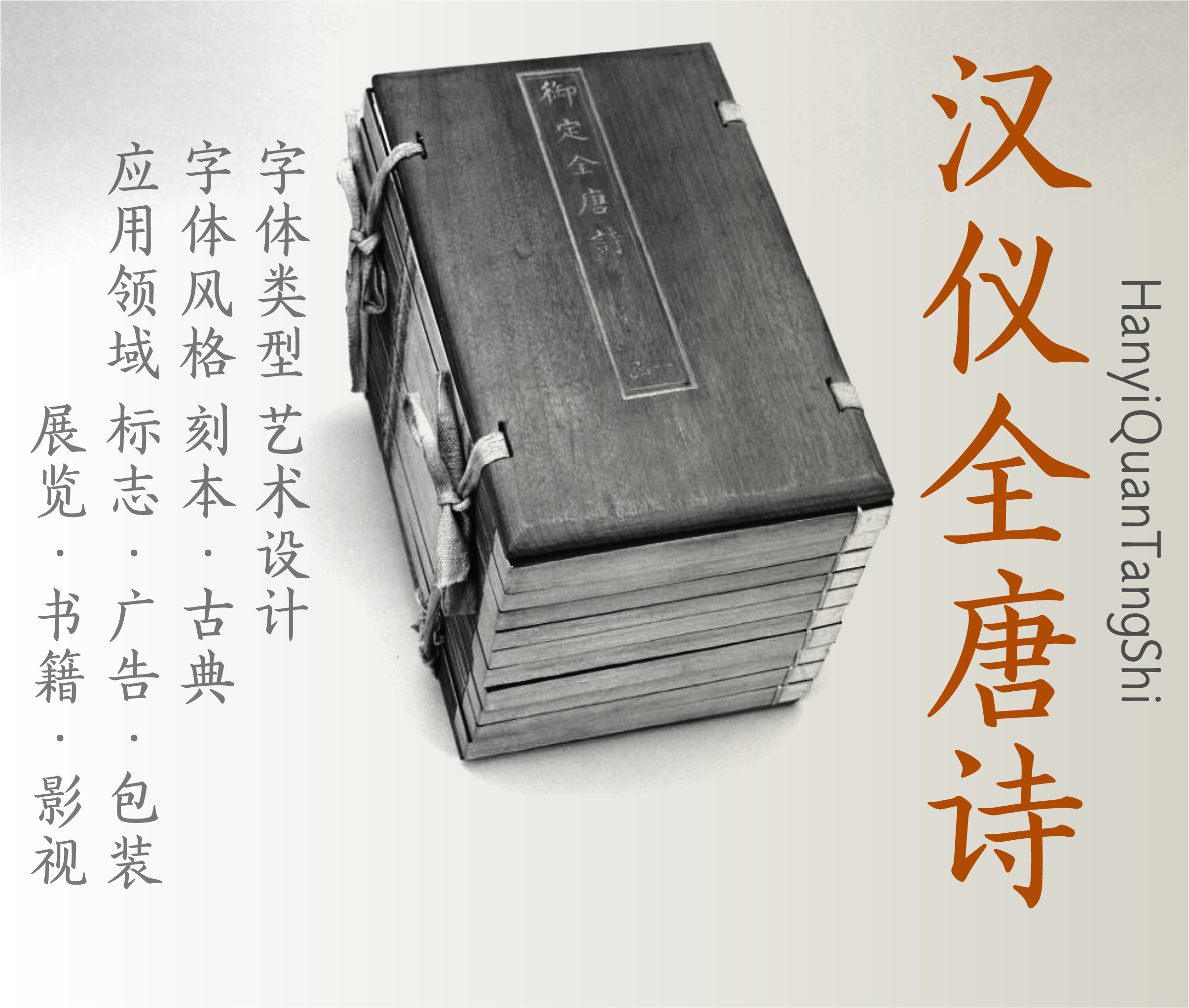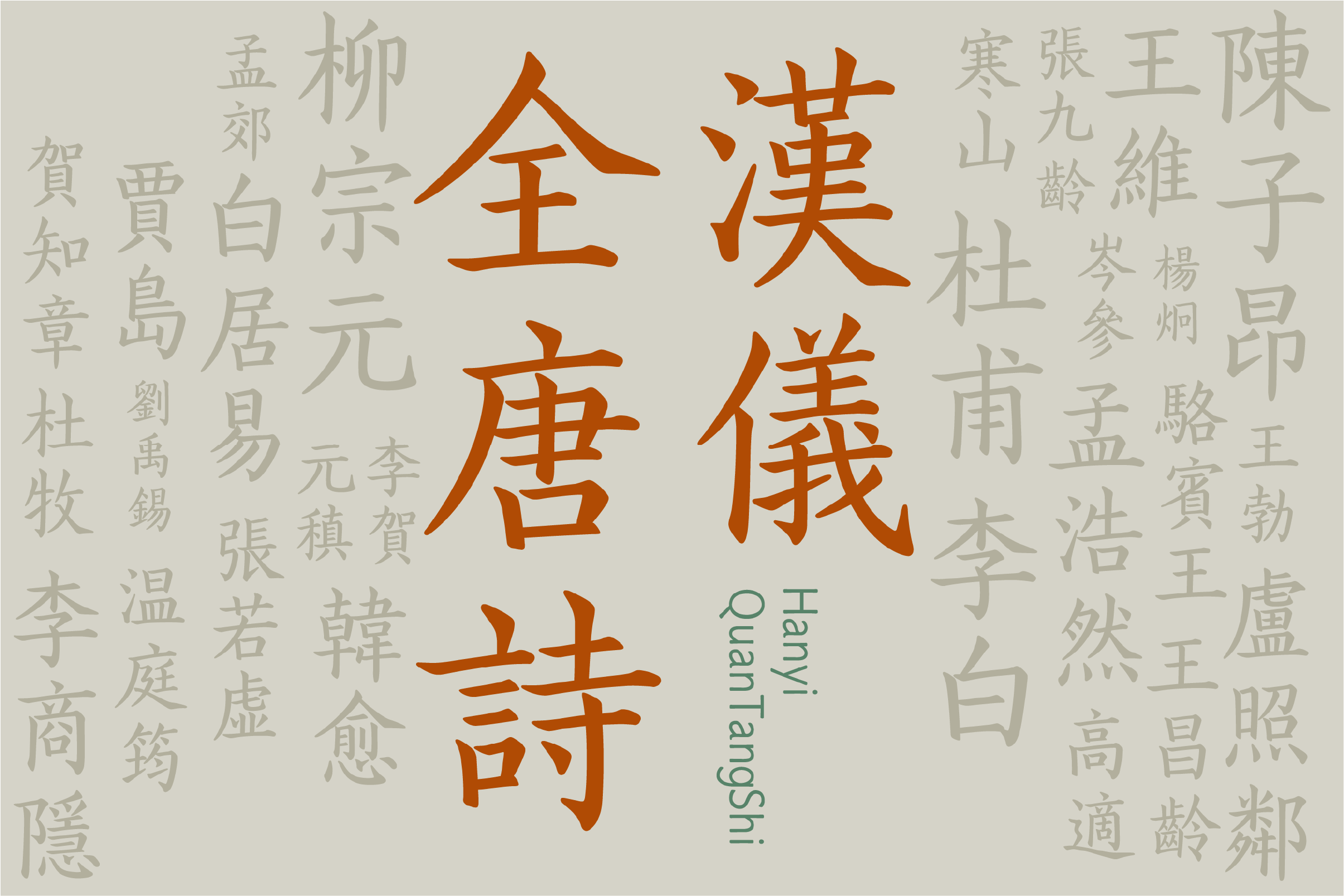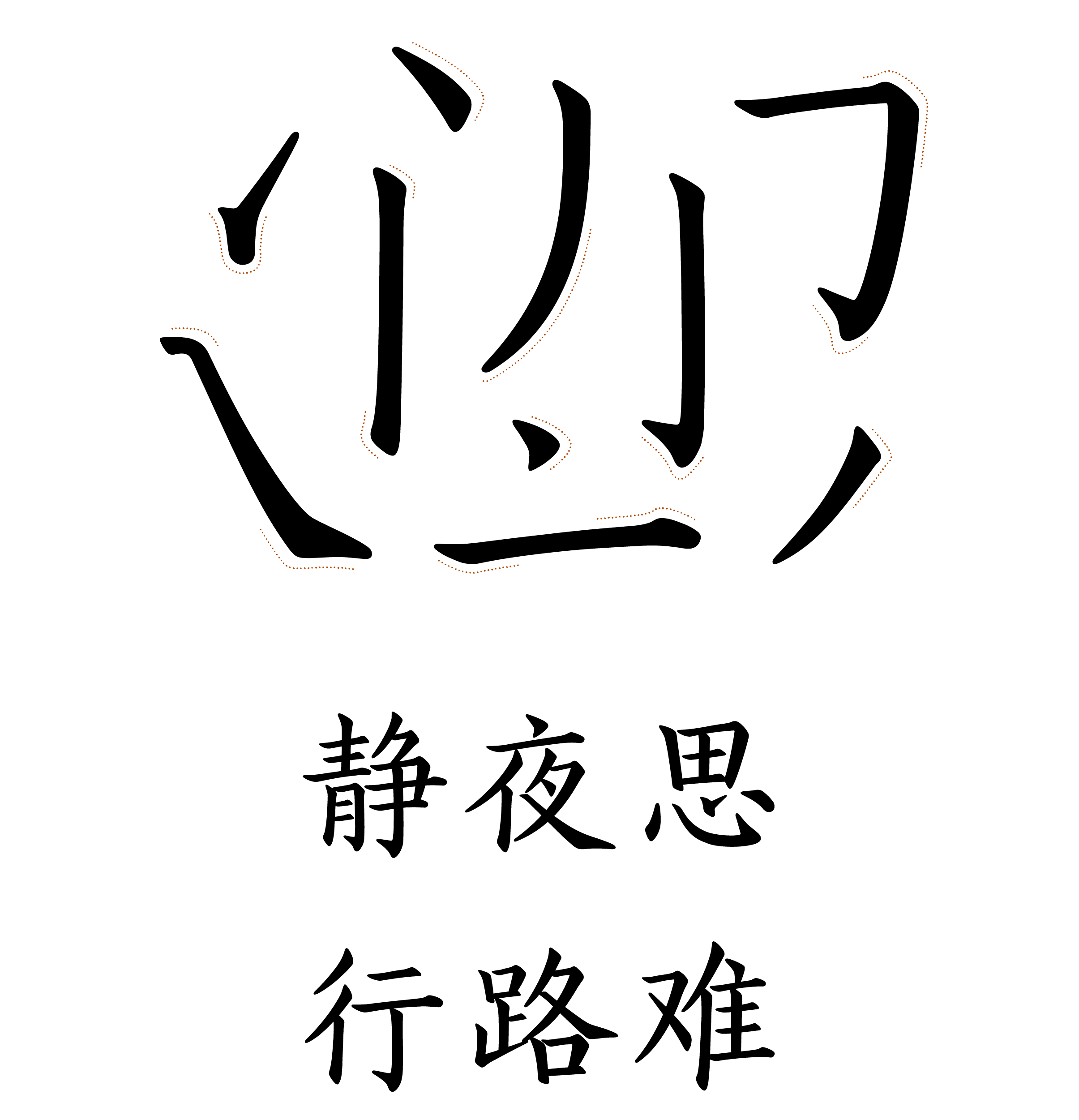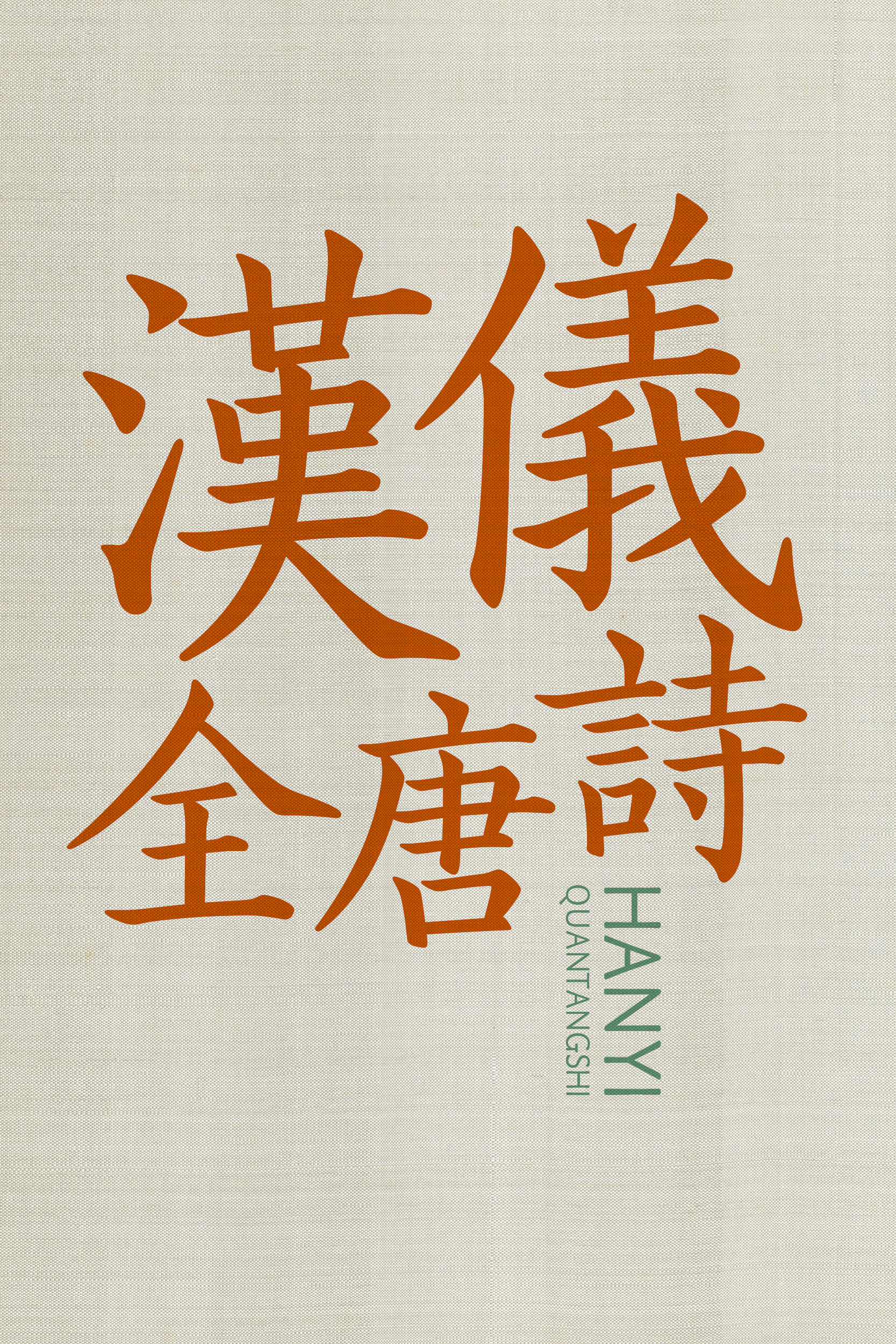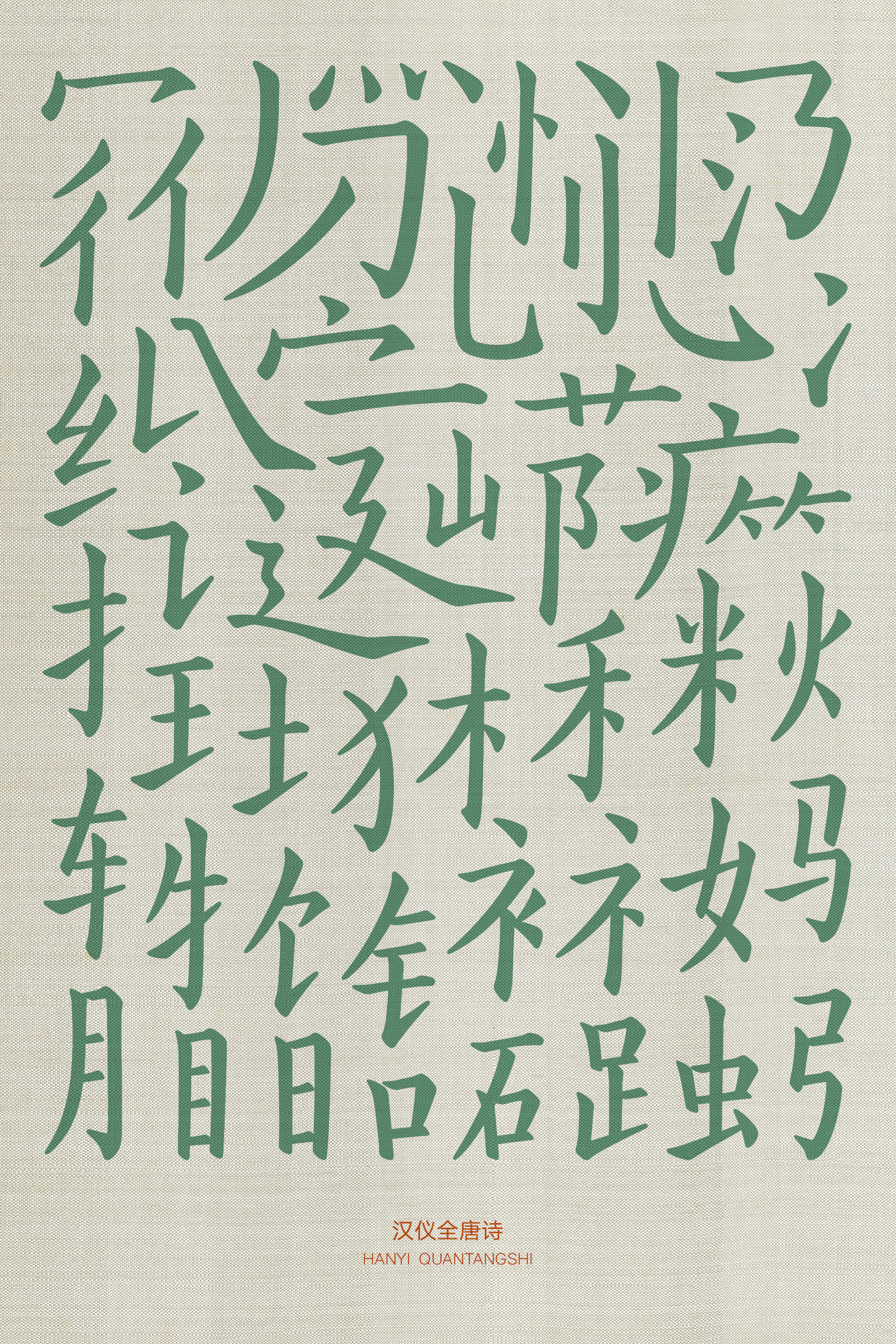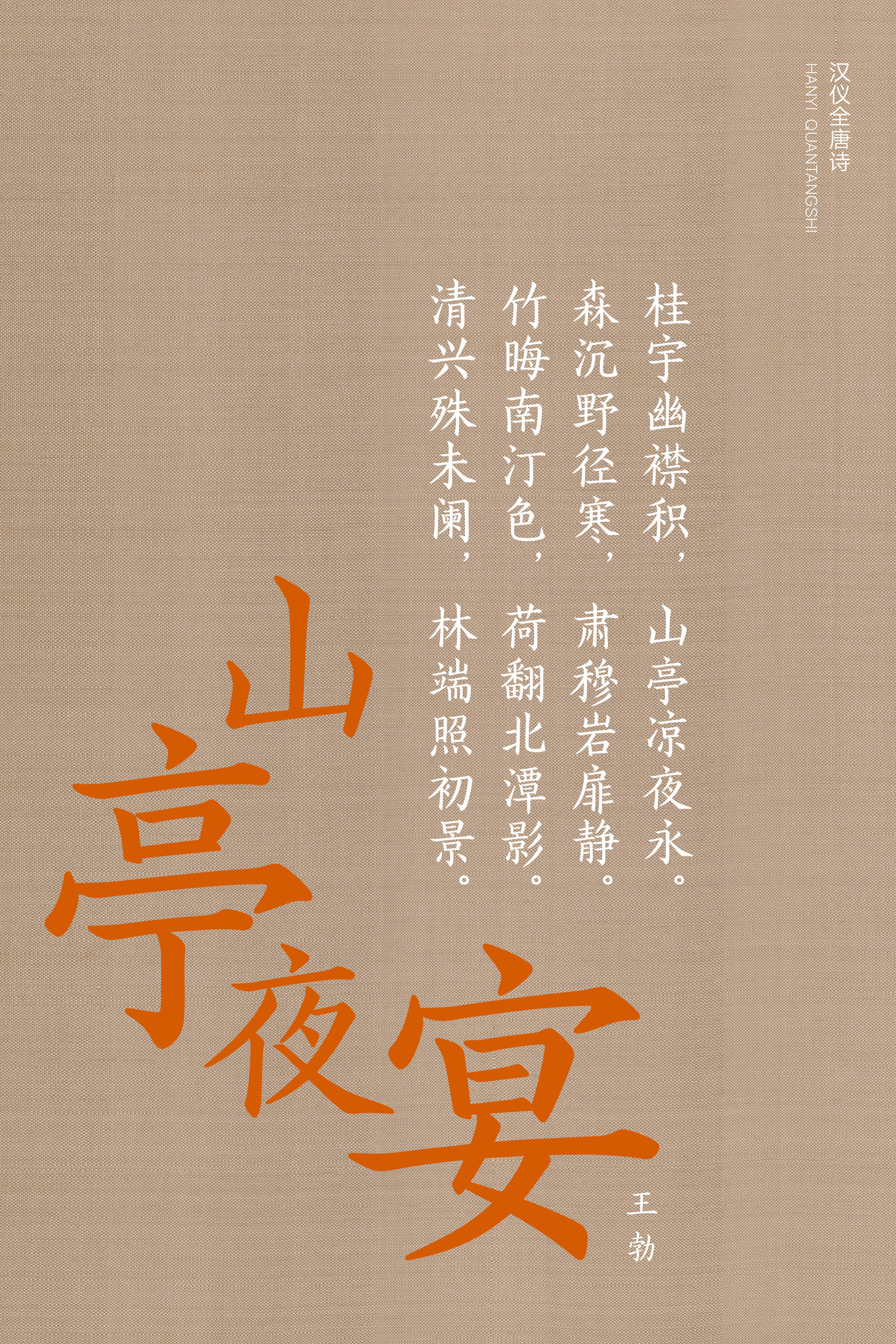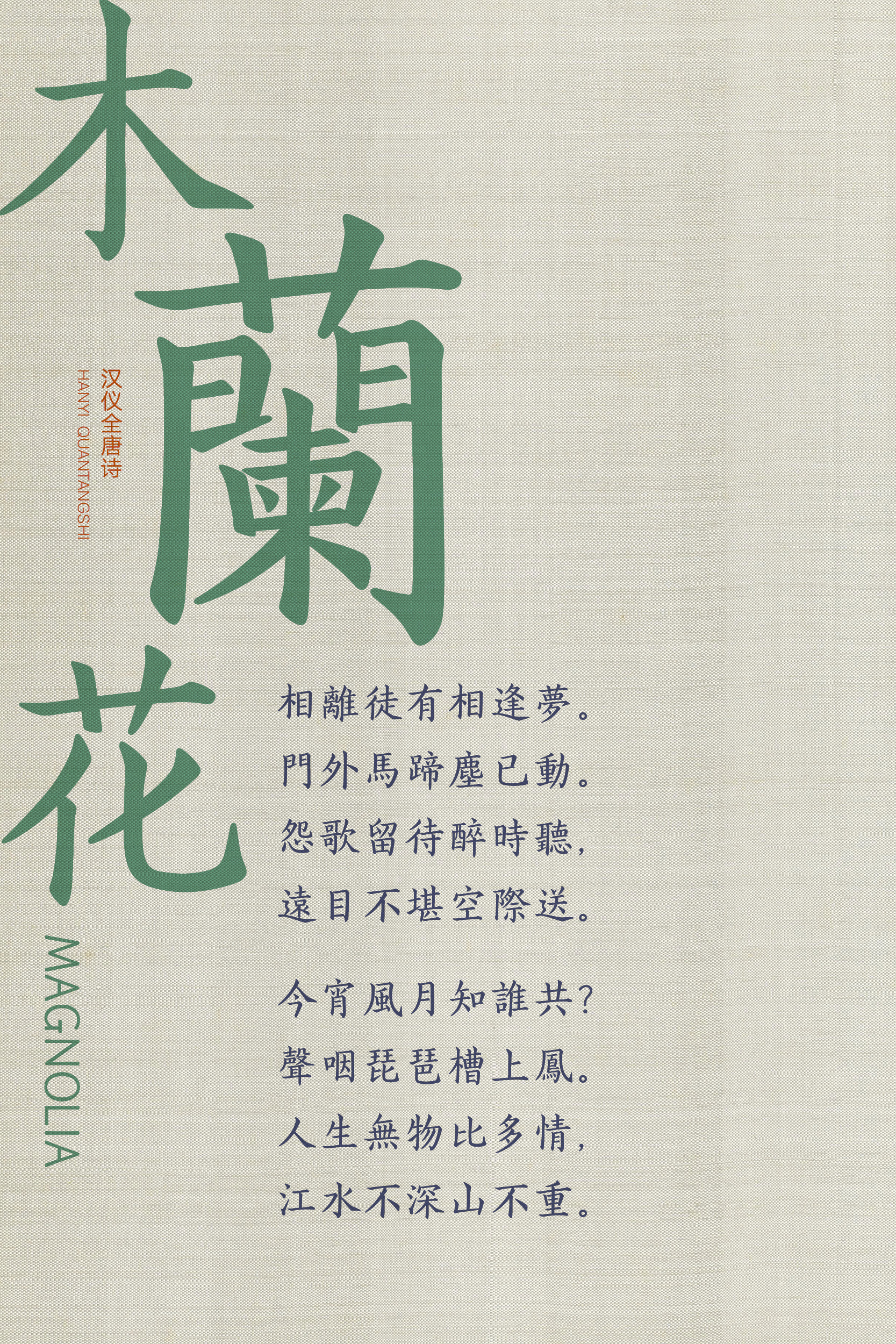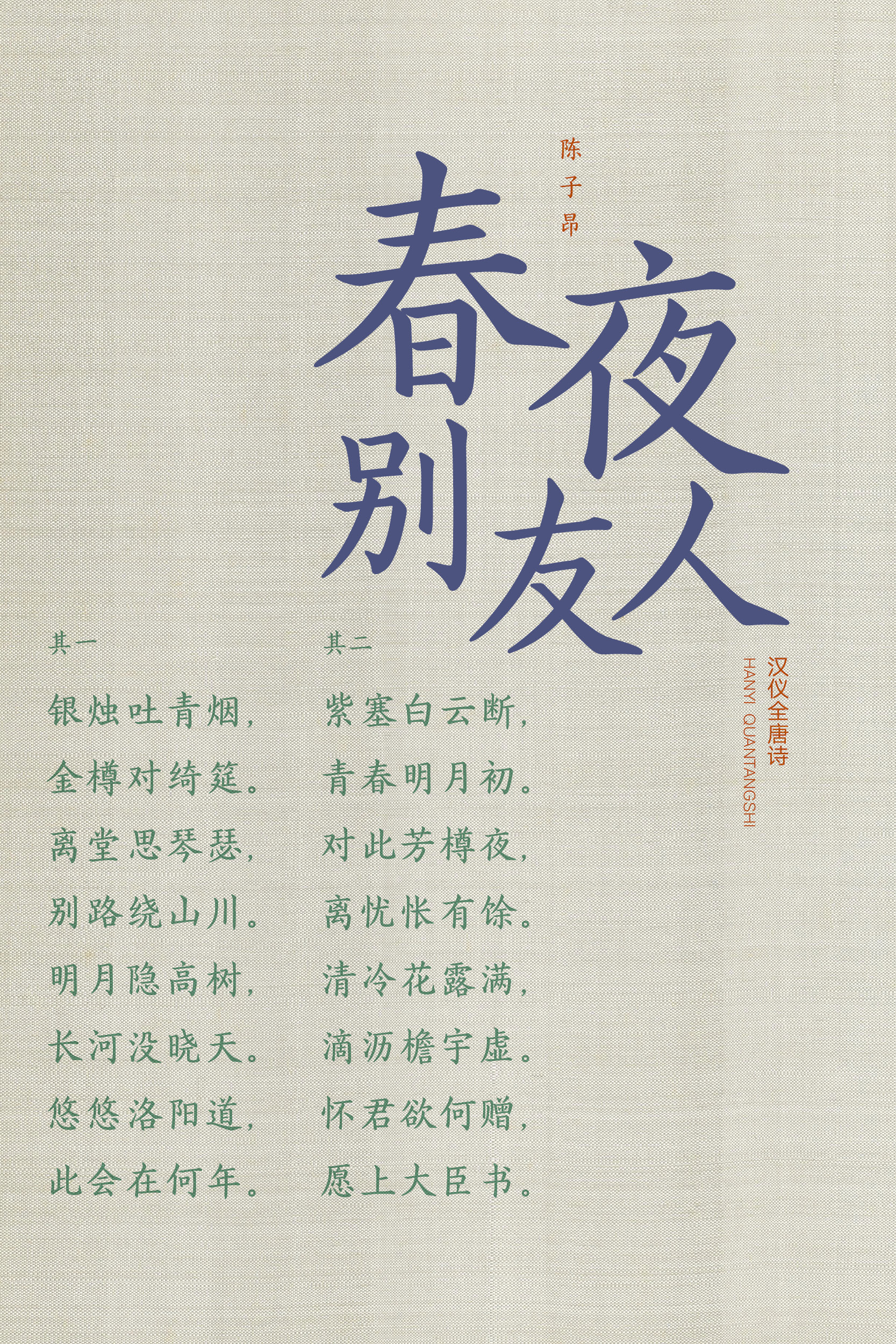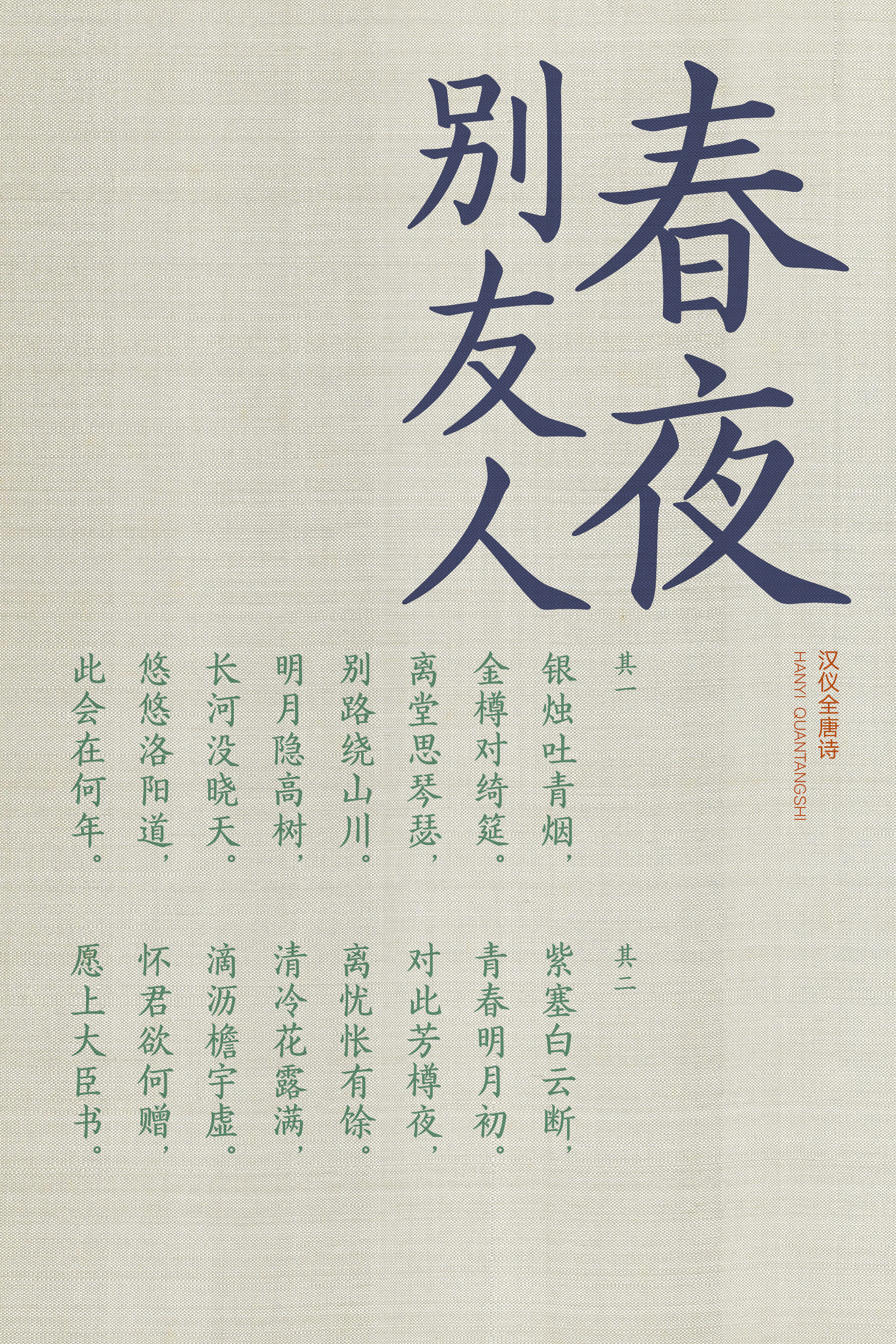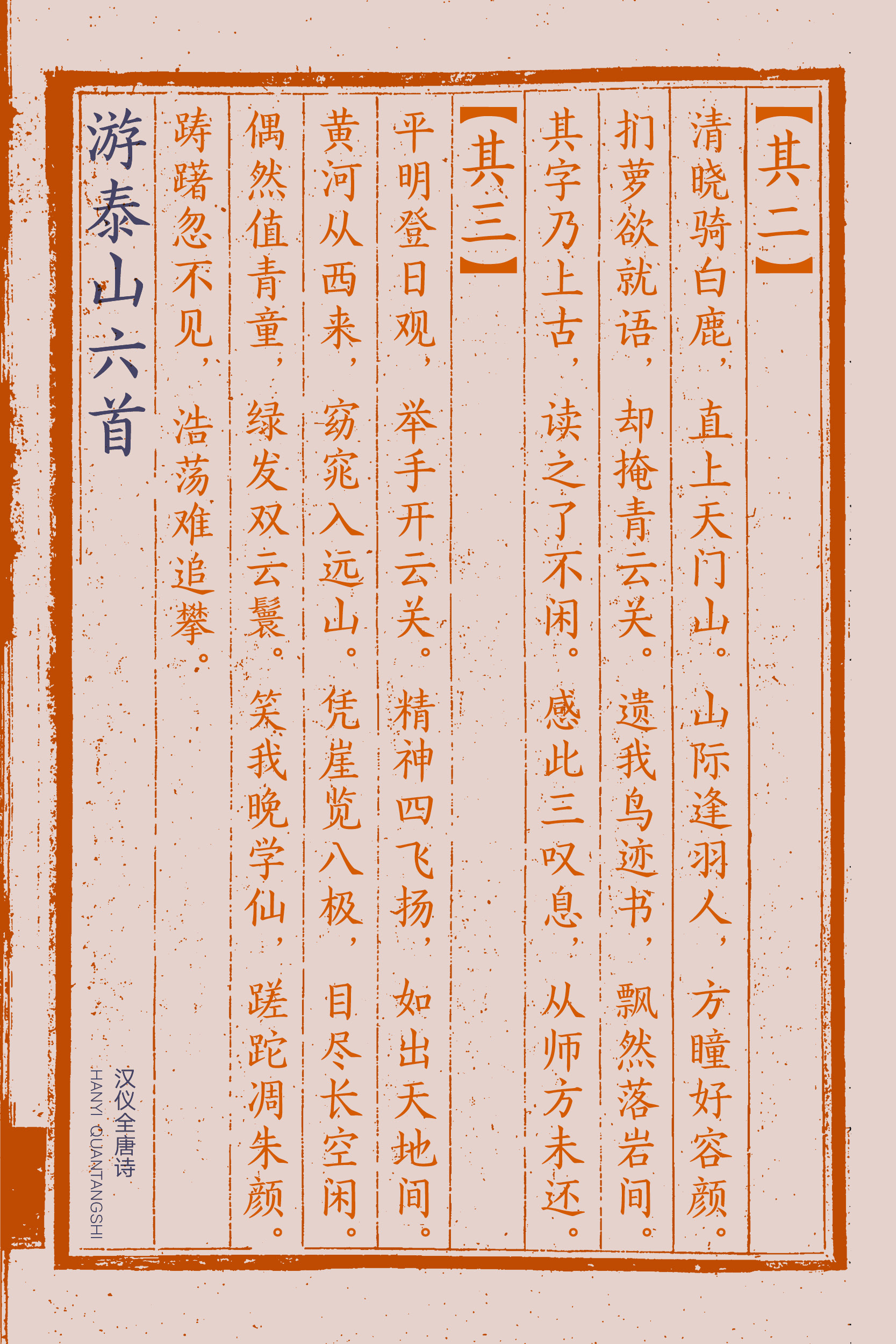
汉仪全唐诗
《全唐诗》,又称《钦定全唐诗》,由清代康熙帝主导,曹寅、彭定求等奉敕编纂,“得诗四万八千九百余首,凡二千二百余人”,共计900卷,目录12卷。此书最早的版本为清康熙四十六年(1707年)的扬州诗局刻本,是清代扬州雕版印刷极盛时期的标志。*
汉仪全唐诗,通过对雕版刻本中字体特征的研习和捕捉,再现康熙版《全唐诗》风貌,不同于简单的复刻,旨在开发一款适用于出版等多领域的高品质全唐诗风格楷体。汉仪全唐诗字形略长,中宫收紧,秀丽圆润,带有写刻味道,气质古典而高雅。一笔一画间体现出写与刻的自然结合,优美而不失力度。
汉仪全唐诗|字体特征
汉仪全唐诗再现了清代扬州雕版印刷的风貌。
字形略长,中宫收紧。
笔画秀丽圆润,带有写刻味道。
汉仪全唐诗的西文部分保留了修长圆润的气质。
汉仪全唐诗|字体样张